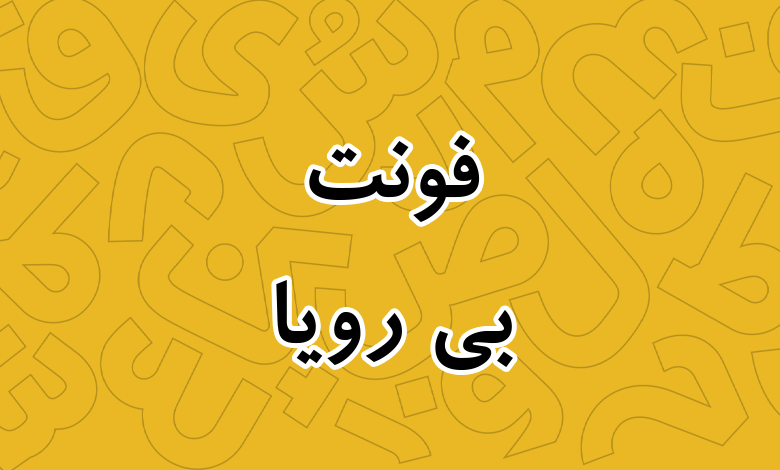
فونت بی رویا (B Roya)
فونت B Roya توسط شرکت برنا رایانه در سبک نسخ طراحی شده است که از دو وزن پشتیبانی میکند. وجود این دو وزن در دورهای که خبری از فونتهای خانوادهدار امروزی با بیش از ۱۰ وزن نبود، در آن دوران مزیت به حساب میآمد. چرا که میتوانستید هم برای عناوین با متون کوتاه و هم برای متون بسیار بلند از این فونت استفاده کنید.
پیشنمایش و امکانات فونت بی رویا (B Roya)
فونت بی رویا آخرین آپدیت خود را در سال ۱۳۷۹ به ورژن ۲.۰۱ دریافت کرده و بیش از دو دهه است که این فونت آپدیت نشده است. از این فونت میتوانید در متونی که جنبه رسمی دارد استفاده کنید. تفاوتی هم ندارد که در نامهنگاری از این قلم بهره ببرید یا اینکه بخواهید برای متون کتاب، مجلات یا حتی روزنامه استفاده کنید.
فونت بی رویا معمولی (Regular) دارای ساختاری نرم و دوستانه است که در متون طولانی خوانایی بسیار خوبی دارد. از سبک نفطهگذاری ناپیوسته لوزی شکل نیز در این قلم استفاده شده است. با اینکه فونت از طراحی نسخ بهره میبرد، اما تا حدودی برخی ویژگیهای خط ثلث نیز در آن دیده میشود؛ از جمله فشرده بودن حروفی همچون «ل، ن» در بخش منحنیها.
فونت بی رویا بولد (Bold) دارای وزنی بیشتر از نسخه معمولی است. ساختار ضخیم این قلم در این وزن طوری است که تا حدودی بهنظر میرسد حروف با زاویه خاصی نسبت به نسخه معمولی ضخیم شده باشند. همین امر به نمایشیتر کردن قلم کمک کرده است.
فونت فارسی بی رویا از این زبان پشتیبانی کاملی دارد؛ به طوری که در بخش اعداد نیز شاهد استفاده از اعداد فارسی در این قلم هستیم. اما اگر مایل به استفاده از فونت بی رویا عربی باشید، باید بگوییم که برای این زبان با محدودیت مواجه خواهید شد. چرا که پشتیبانی از زبان عربی محدود به حروف فارسی بوده و برخی حروف استاندارد عربی را که شامل دو نقطه در زیر یا بالای حروف هستند ندارد.
برای زبان انگلیسی نیز گلیف اختصاصی برای این فونت در نظر گرفته نشده و از همان فونت پیشفرض استفاده خواهد شد. بنابراین توصیه میشود اگر بهدنبال فونتی در این سبک برای سایر زبانها هستید، فونت دماوند را بررسی کنید.